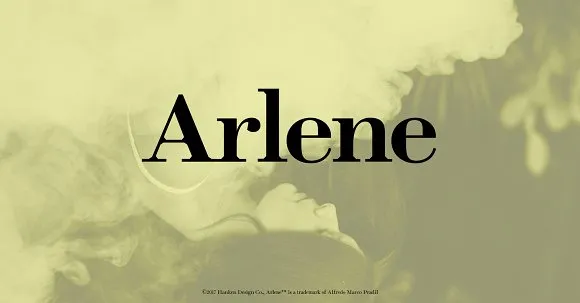
A Arlene™ é uma fonte com alta contraste que inclui braços angulares perfeitos para aplicações de destaque, títulos e posters. Suas linhas aguçadas criam um visual intrigante e vibrante, tornando-a ideal para ambientes onde o destaque é fundamental. Ela vem em várias opções de peso: regular, semi-bold, bold e black. Esta fonte moderna e atraente será uma escolha perfeita para criar uma identidade visual única e diferenciada. Sua simplicidade combinada com um toque moderno tornam a Arlene™ uma escolha inteligente tanto para projetos digitais quanto impressos, desde o design de logotipos até as capas de revistas.